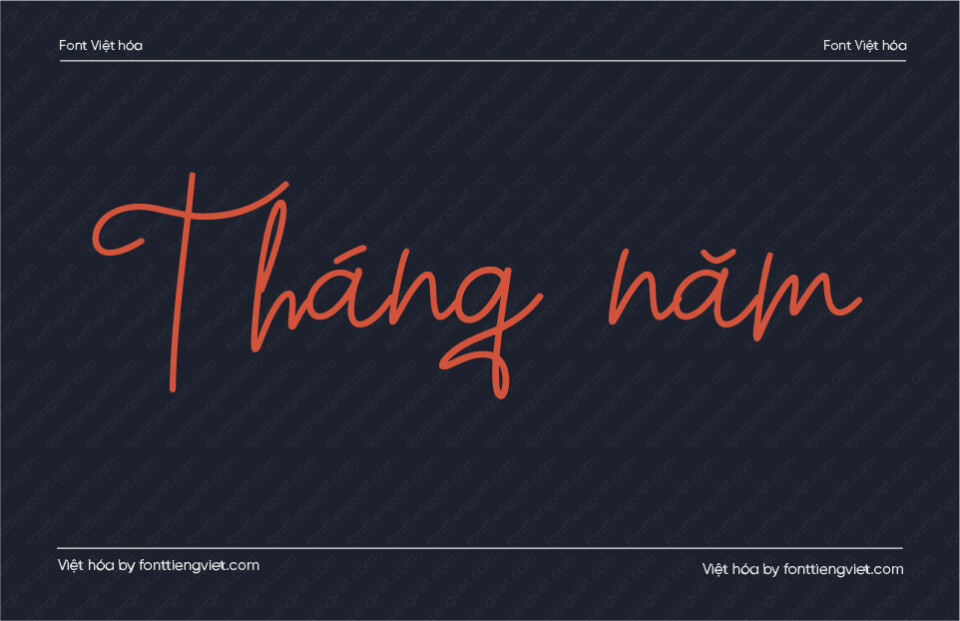
Font Việt hóa 1FTV VIP Tranquil Dream Script: Nét Chữ Mềm Mại Cho Thiết Kế Ý Nghĩa
Trong thế giới thiết kế đồ họa, việc lựa chọn một Font Chữ phù hợp đóng vai trò then chốt trong việc truyền tải cảm xúc. Font Việt hóa 1FTV VIP Tranquil Dream Script là một bộ phông chữ viết tay nghệ thuật, mang phong cách bay bổng và tinh tế. Với đường nét uyển chuyển, bộ phông này đặc biệt phù hợp cho các dự án sáng tạo cần sự nhẹ nhàng, từ thiệp mời, bìa sách đến các ấn phẩm truyền thông học đường.
Ưu điểm nổi bật của Font Việt hóa 1FTV VIP Tranquil Dream Script
Bộ font này sở hữu những đặc điểm độc đáo giúp người dùng dễ dàng tạo nên những tác phẩm ấn tượng. Cấu trúc chữ được thiết kế tỉ mỉ, đảm bảo tính thẩm mỹ cao mà vẫn giữ được sự rõ ràng khi đọc.
Khả năng hiển thị tiếng Việt hoàn hảo
Điều làm nên giá trị của Font Việt hóa 1FTV VIP Tranquil Dream Script chính là sự tương thích tuyệt đối với tiếng Việt. Các dấu thanh được đặt vị trí chuẩn xác, tránh tình trạng lỗi font hay chồng chéo chữ thường gặp ở các bản phông chữ nước ngoài. Điều này giúp các giáo viên và học sinh dễ dàng sử dụng trong việc thiết kế slide bài giảng hoặc làm báo tường sinh động.
Ứng dụng linh hoạt trong thiết kế hiện đại
Với phong cách Script thanh lịch, phông chữ này không chỉ giới hạn trong các thiết kế truyền thống. Bạn có thể sử dụng nó để làm watermark cho ảnh, thiết kế logo thương hiệu cá nhân hoặc tạo các trích dẫn truyền cảm hứng trên mạng xã hội. Sự kết hợp giữa nét chữ thanh mảnh và độ nghiêng tự nhiên tạo cảm giác gần gũi và chân thực.
Để phát huy tối đa vẻ đẹp của phông chữ này, bạn nên kết hợp với các font không chân (Sans Serif) đơn giản để tạo sự cân bằng. Việc sử dụng màu sắc nhẹ nhàng như pastel sẽ làm tôn lên vẻ yên bình đúng như tên gọi “Tranquil Dream”.